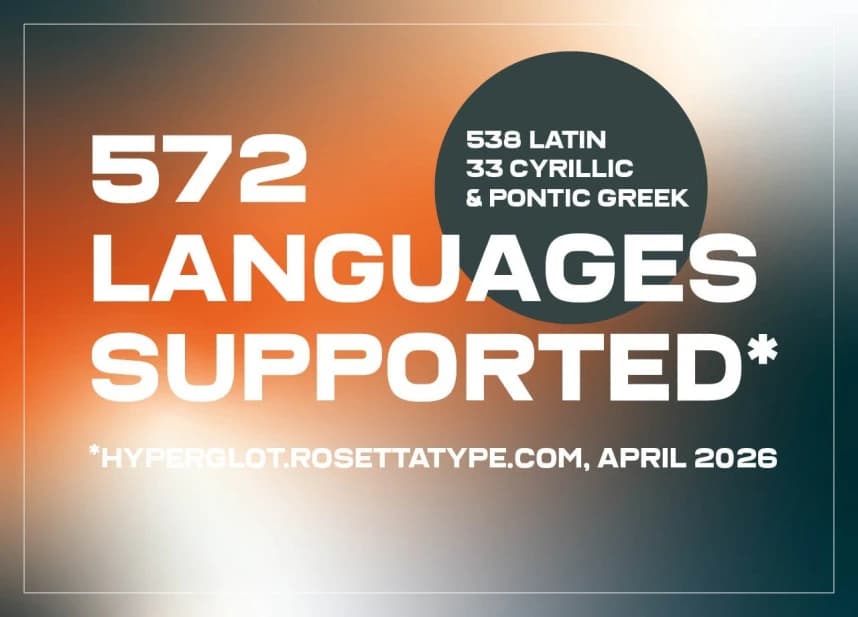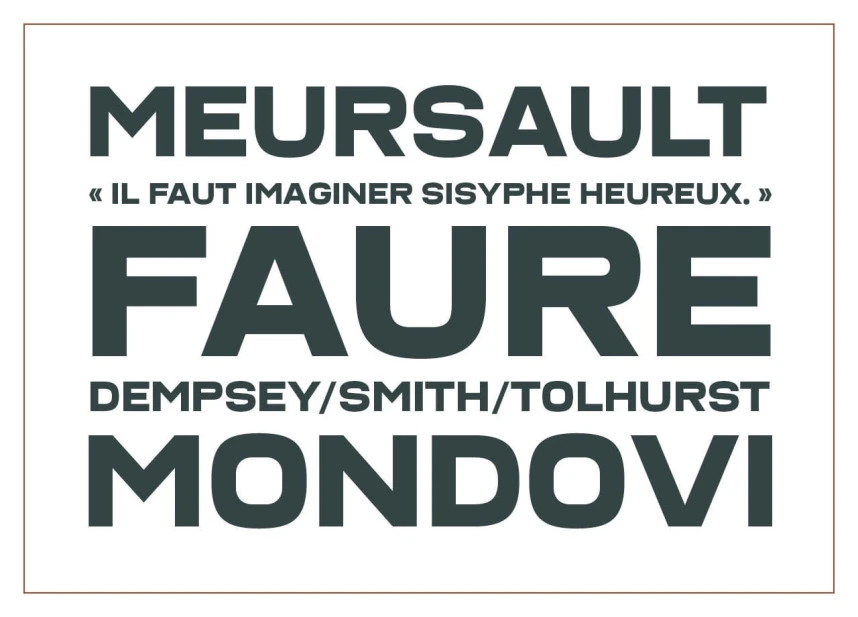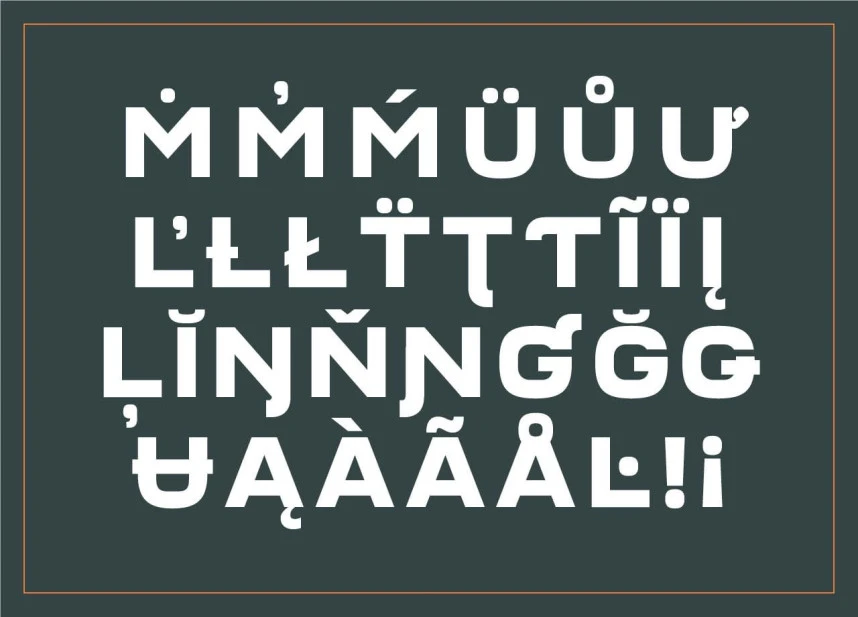
Dunkerque Font, tamamen büyük harflerden oluşan bir yazı tipidir ve cesur ile akılda kalıcı bir etki yaratmak üzere tasarlanmıştır. Güçlü ve yapılandırılmış harf biçimleri güven ve kuvvet hissi verir; bu da başlıklar, logolar ve öne çıkması gereken markalaşma çalışmaları için idealdir.
Dunkerque Font, cesur ve akılda kalıcı bir etki yaratmak için tasarlanmış tüm büyük harflerden oluşan bir yazı tipidir. Güçlü, yapılandırılmış harf biçimleri güven ve güç duygusunu ifade eder; bu da başlıklar, logolar ve öne çıkması gereken marka kimliği için idealdir.